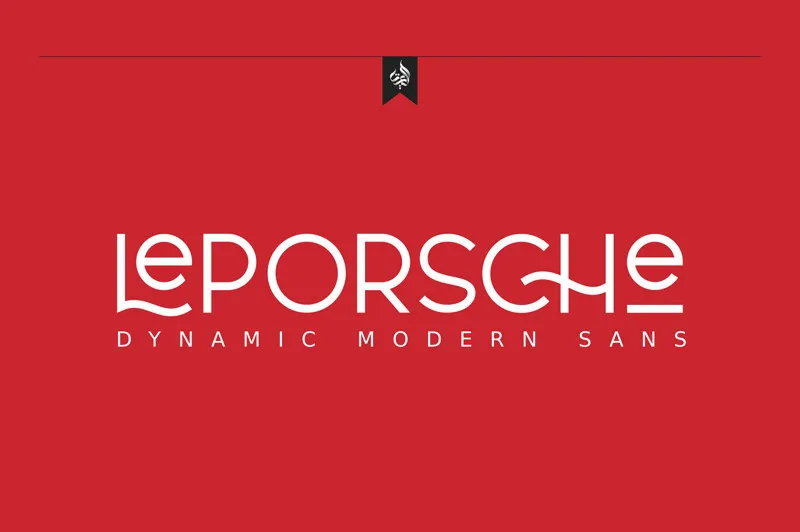
AL LePorsche Retro Font
A AL LePorsche Retro Font é uma elegante fonte moderna sem serif que traz muitas alternativas estilizadas ao seu dispor. É uma fonte versátil que se adapta perfeitamente tanto em tamanhos grandes quanto pequenos. Suas linhas limpas e minimalistas tornam-na ótima para uso em logotipos, headlines, panfletos, embalagens e muito mais. Seu design simples e funcional combina perfeitamente sozinho ou com outros elementos de design para criar trabalhos gráficos atraentes e profissionais. Se você está buscando uma fonte que possa atender às necessidades de um projeto variado, esta é provavelmente uma ótima escolha.